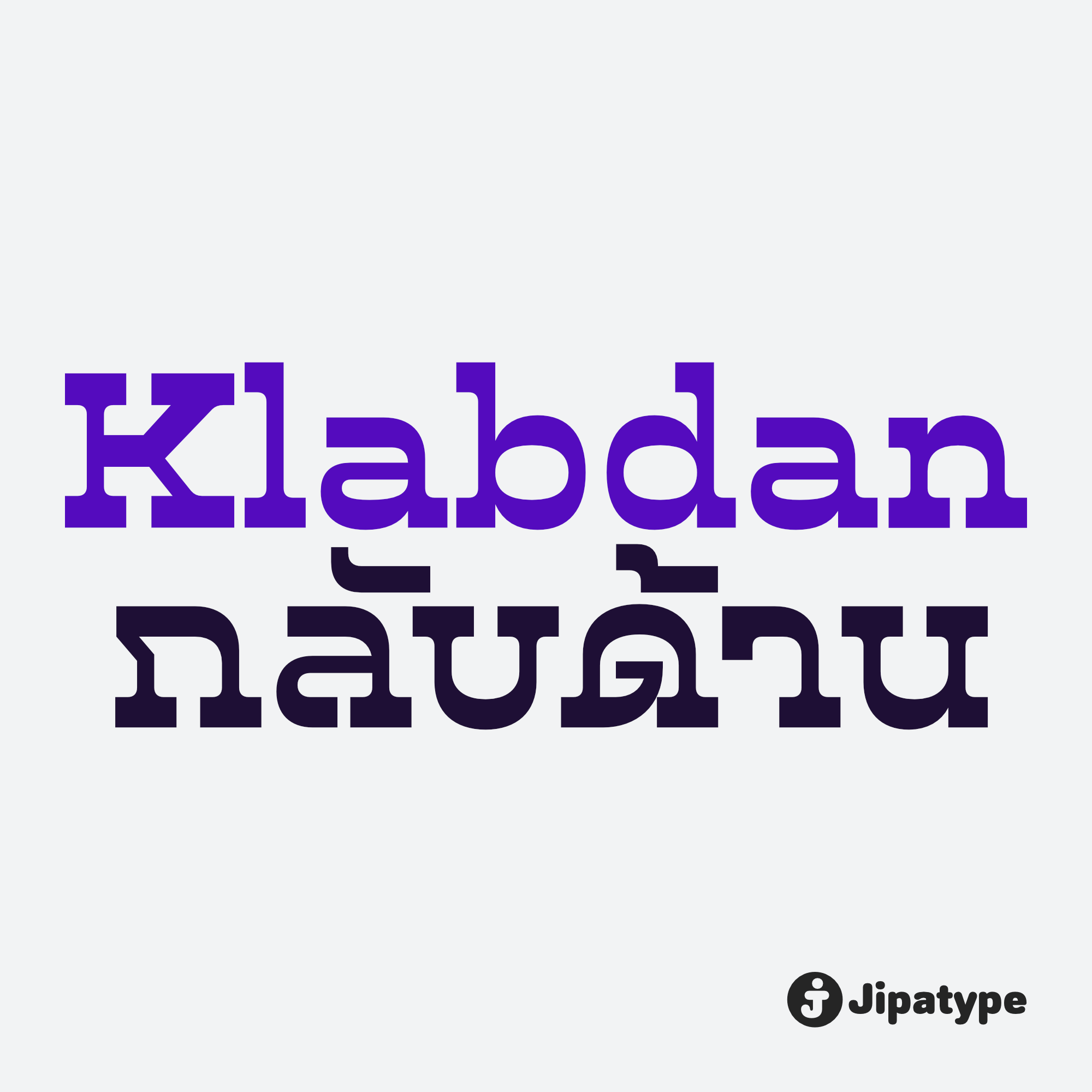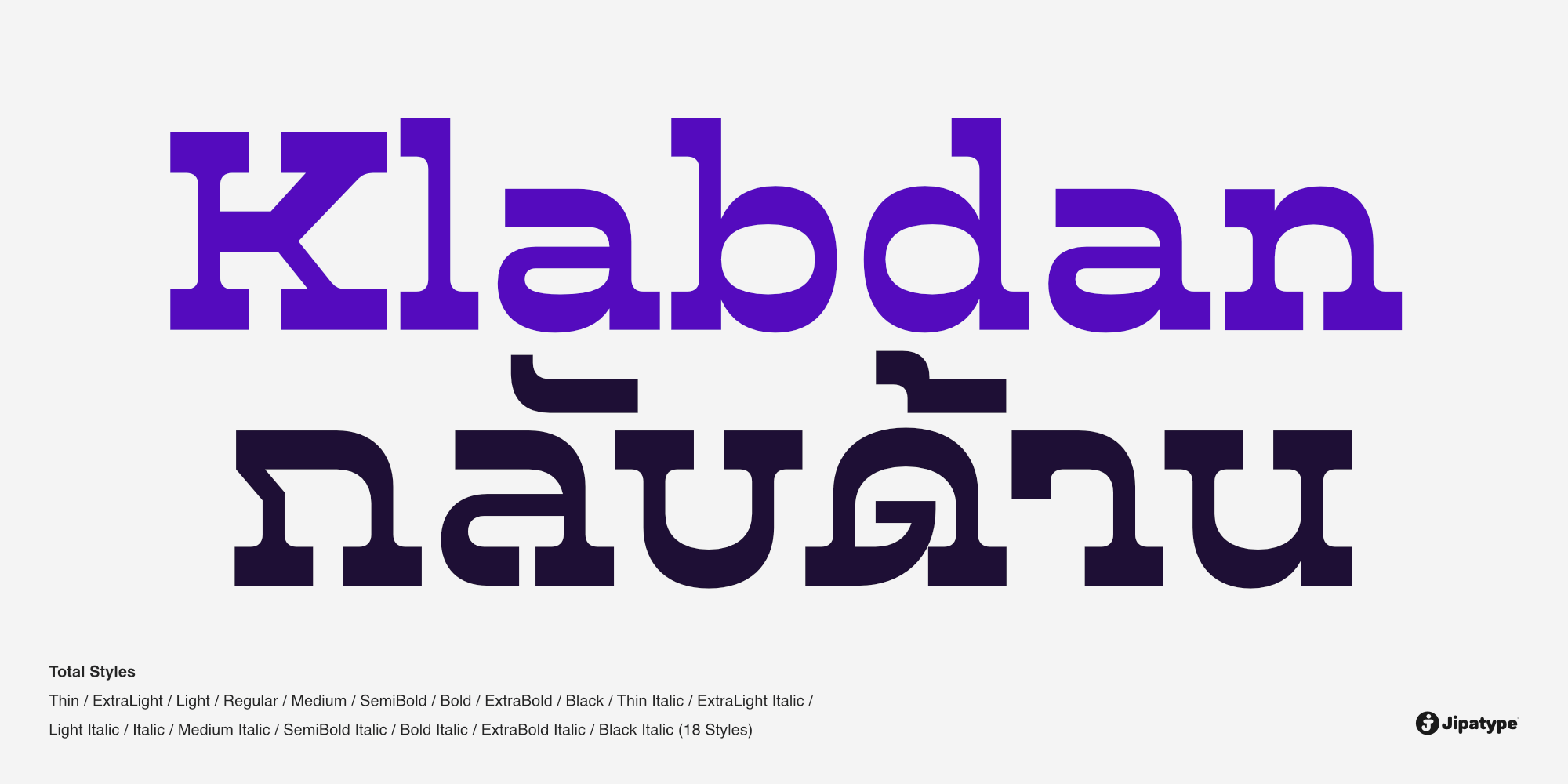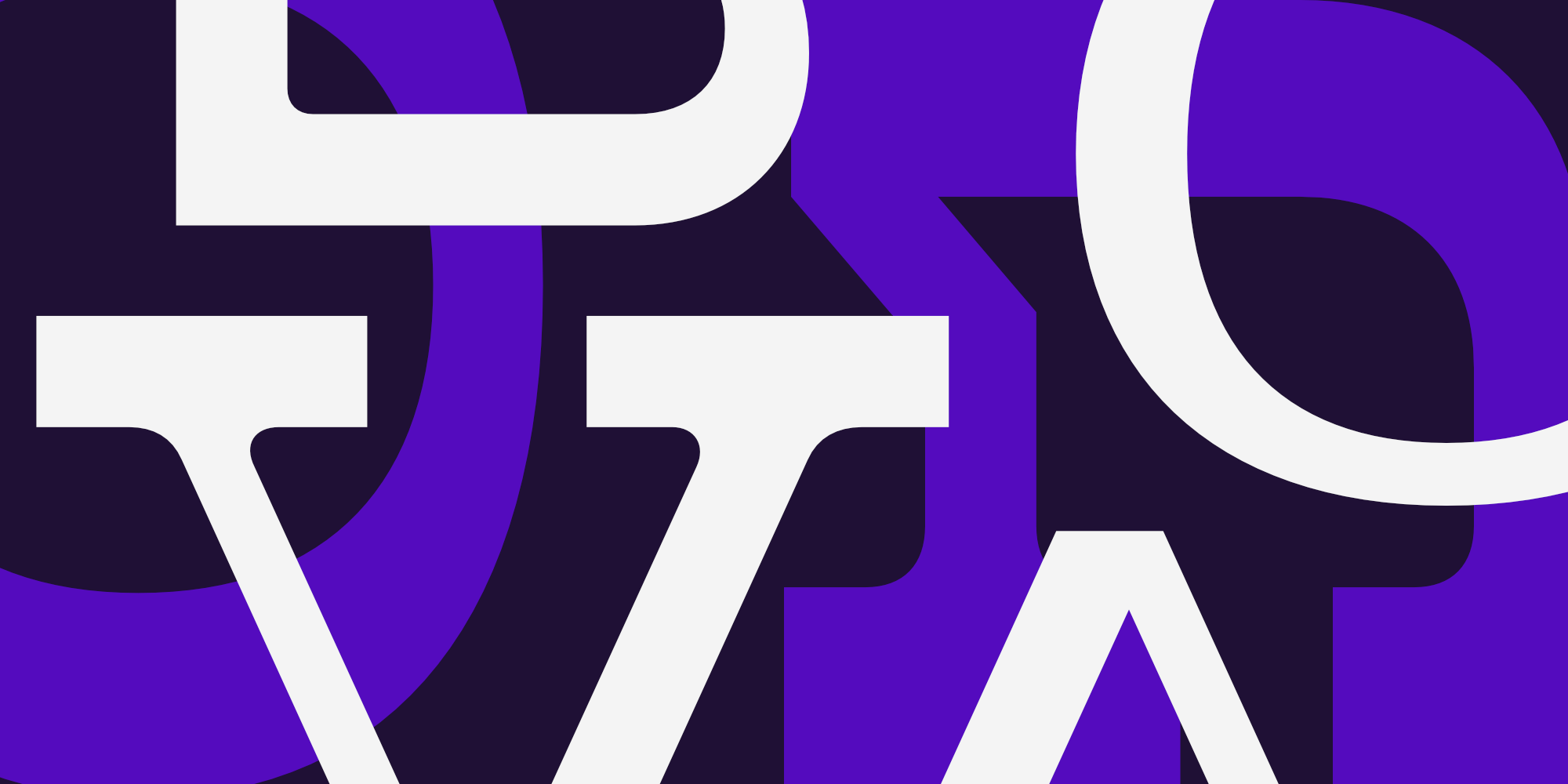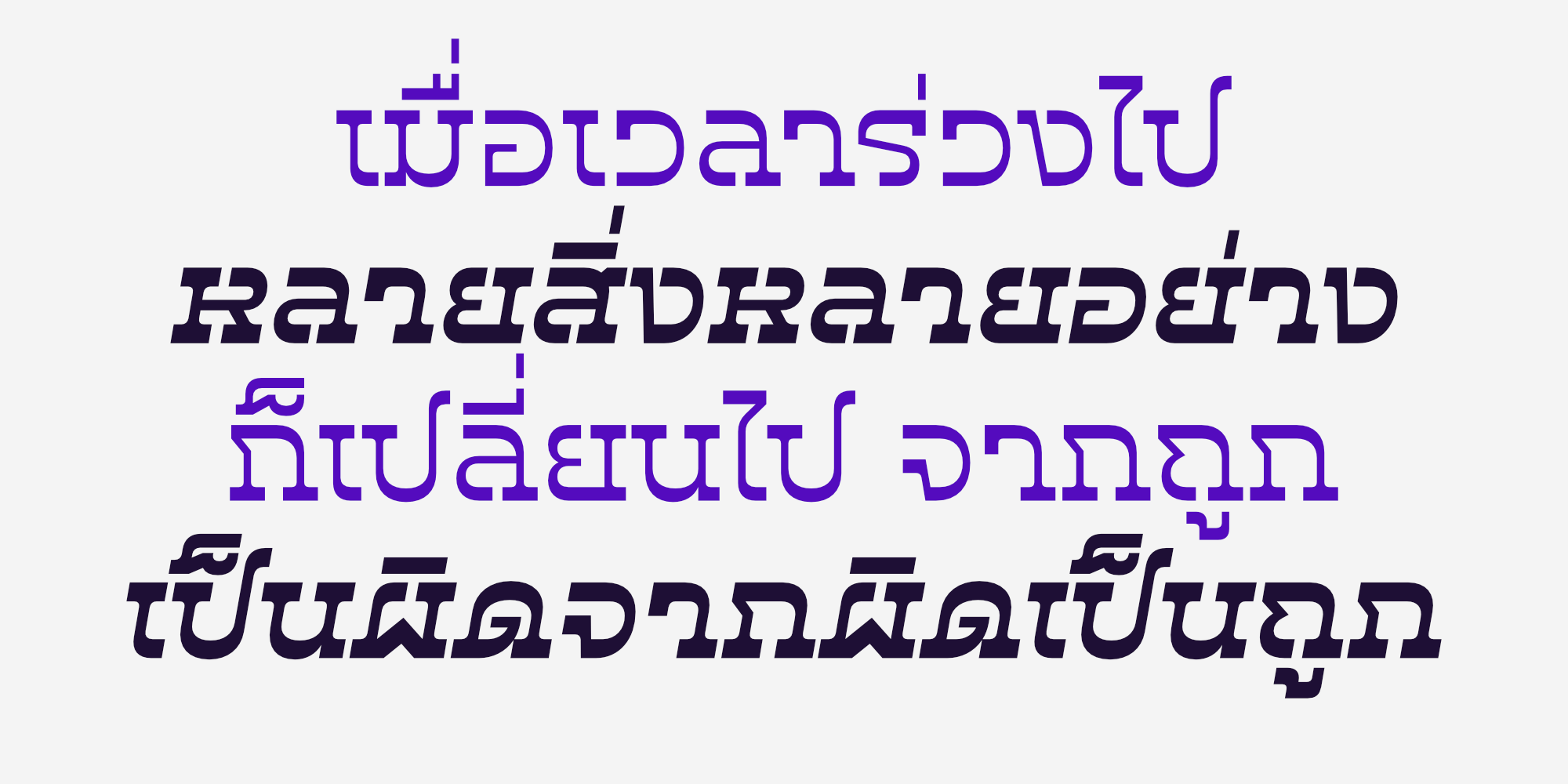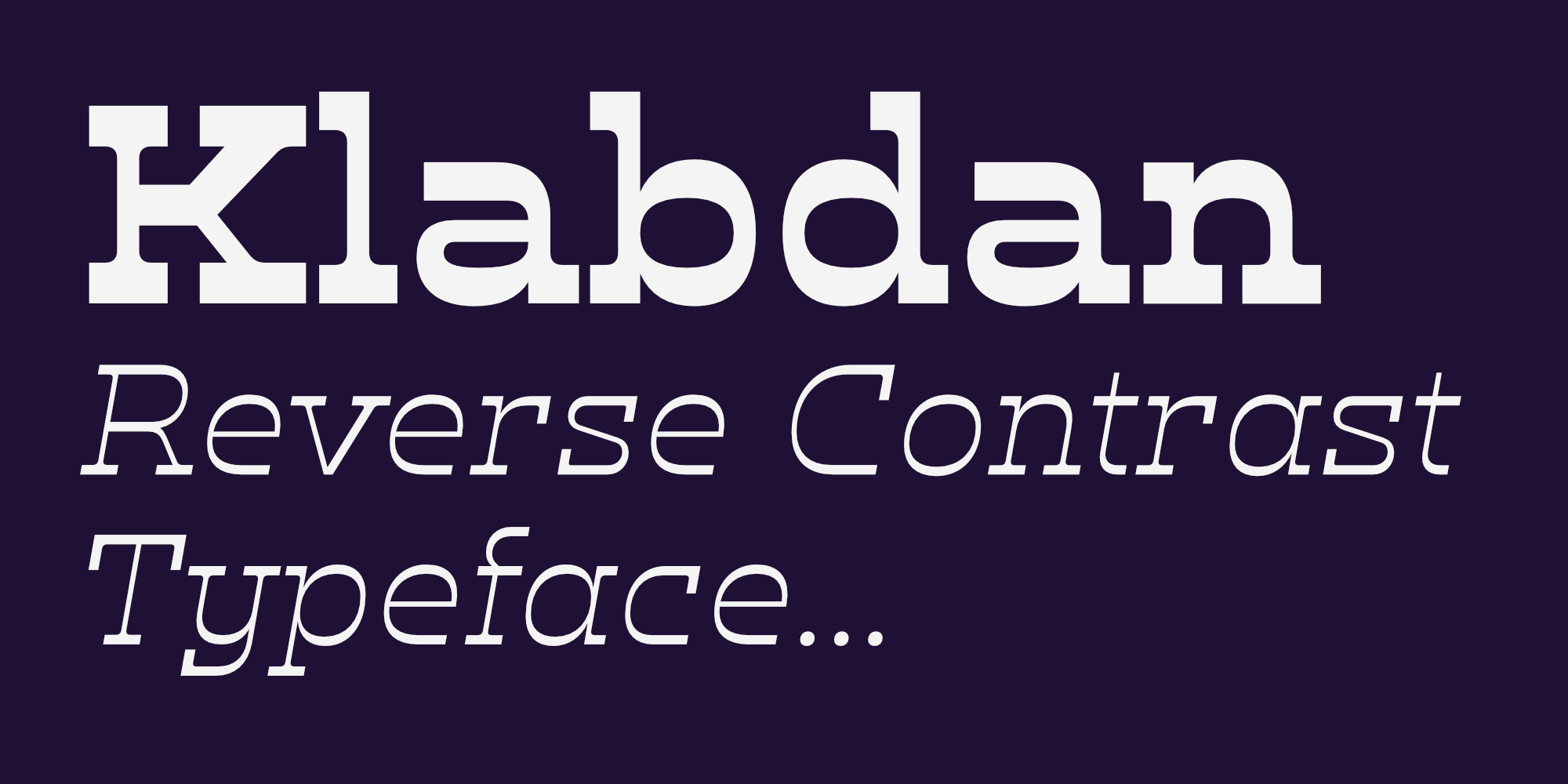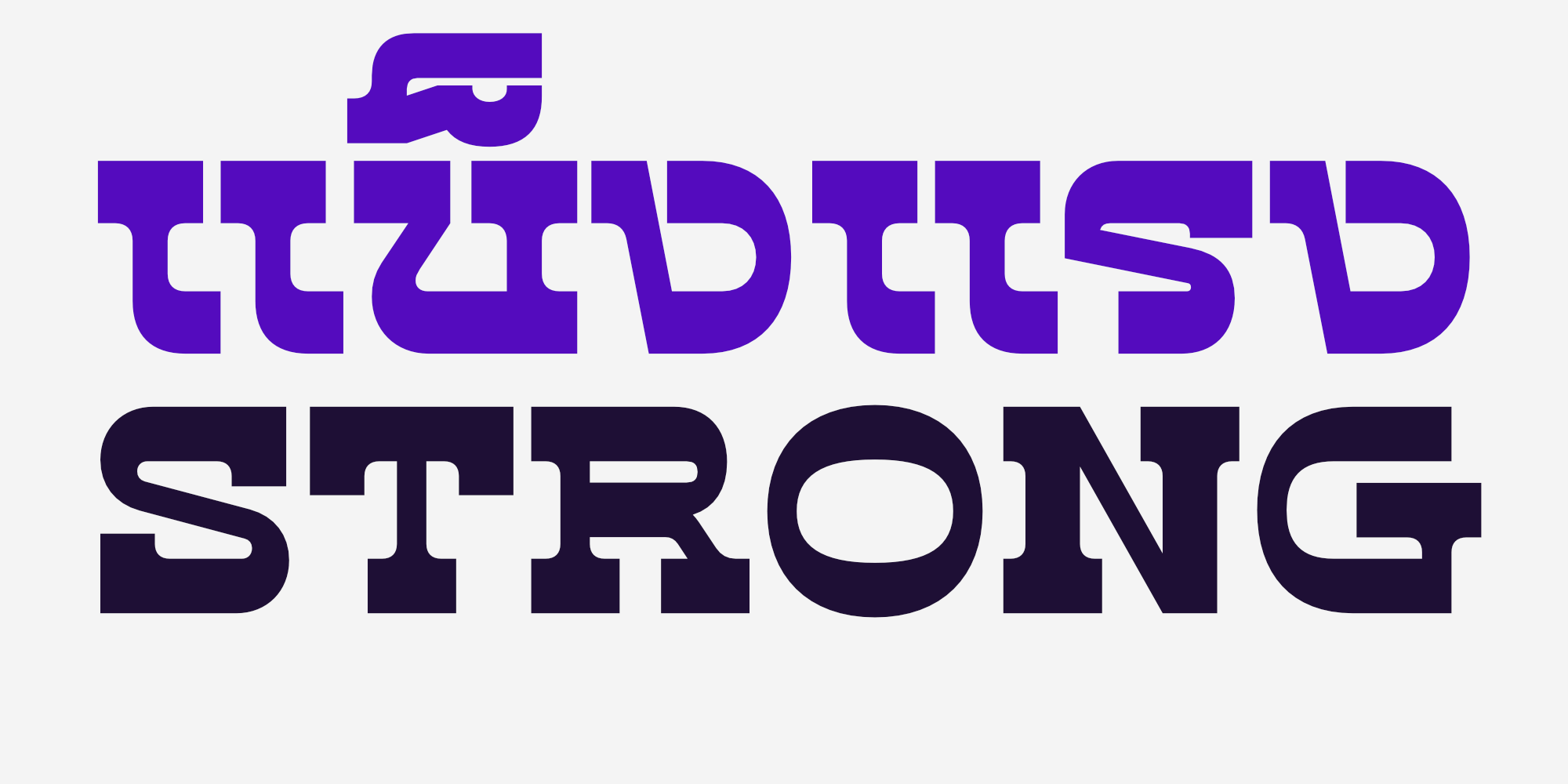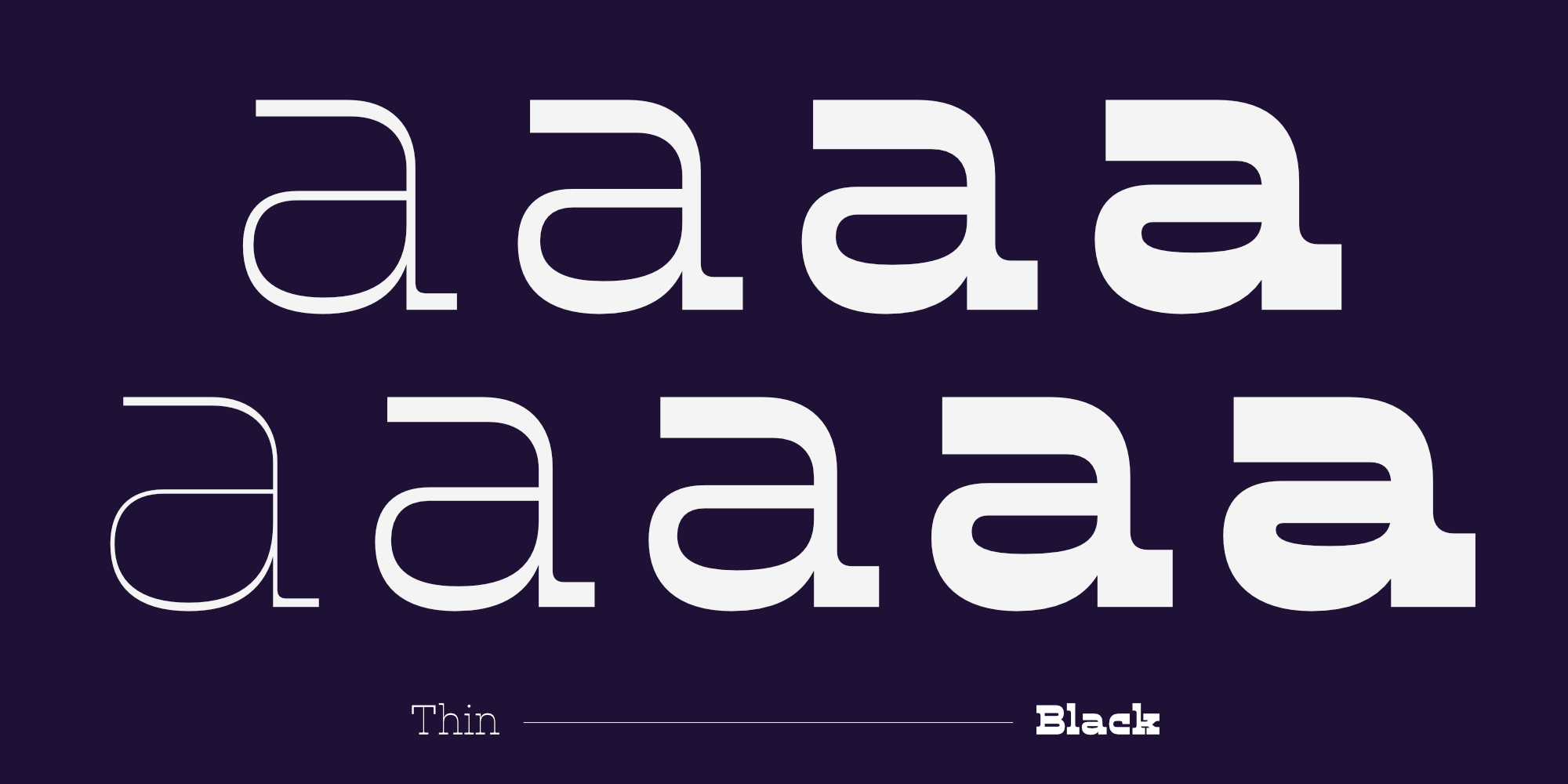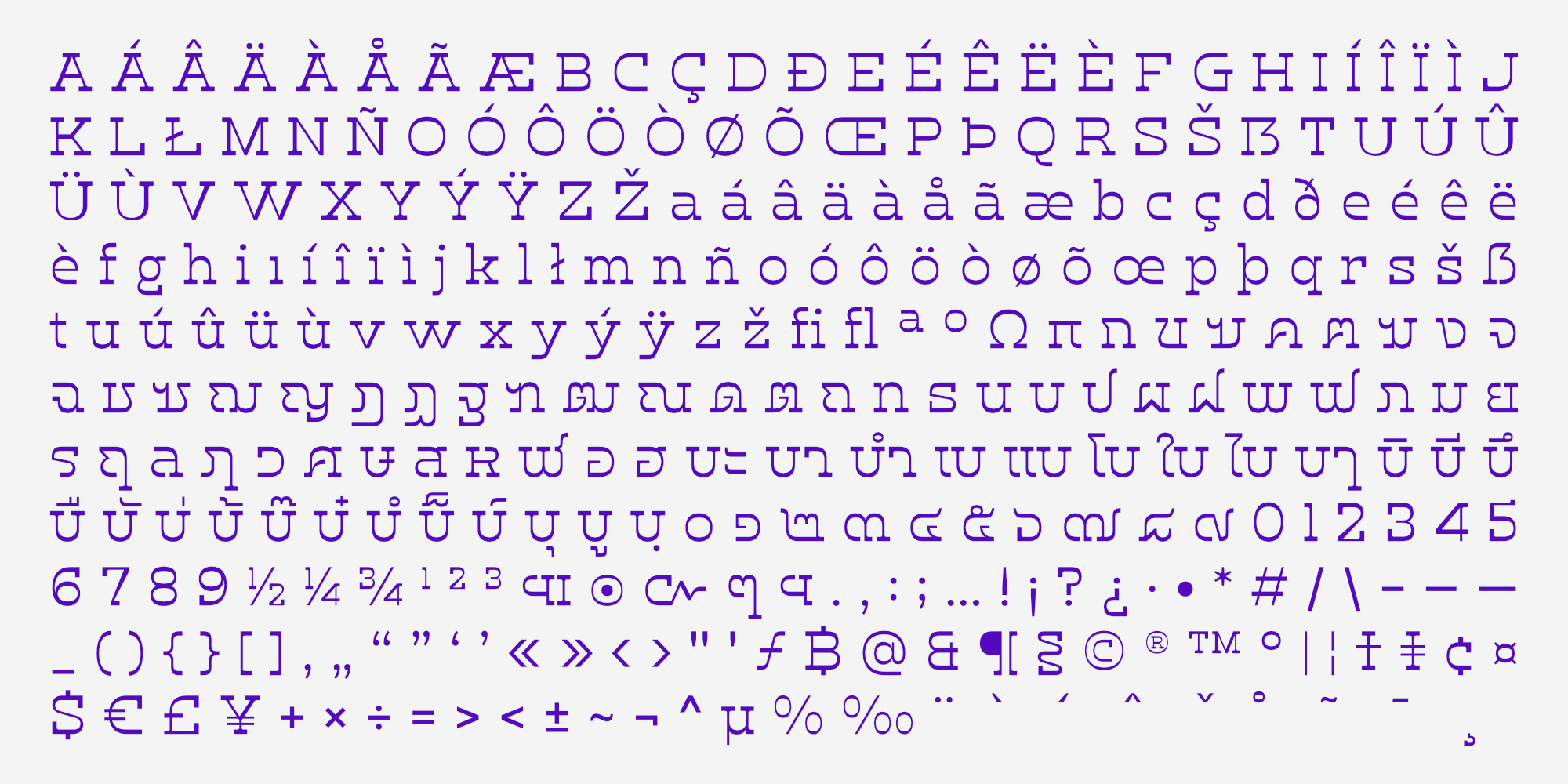
Klabdan (กลับด้าน) เป็นชุดตัวอักษรประเภท Reverse Contrast Slab Serif ที่มีเอกลักษณ์เฉพาะตัวสูง ด้วยการออกแบบที่ฉีกกฎเกณฑ์เดิม ๆ โดยการเน้นน้ำหนักของเส้นแนวนอนให้หนาและเส้นแนวตั้งให้บาง ประกอบกับฐานตัวอักษรแบบ Slab Serif ที่มีความโค้งมนเล็กน้อย ช่วยลดความแข็งกระด้างและเพิ่มความรู้สึกเป็นมิตร
ตัวฟอนต์ให้กลิ่นอายผสมผสานระหว่างความย้อนยุค และความร่วมสมัยที่ดูสนุกสนาน มาพร้อมกับชุดตัวอักษรภาษาไทยที่ได้รับการออกแบบให้มีสไตล์สอดคล้องกับตัวละตินอย่างลงตัว ทำให้ Klabdan เหมาะอย่างยิ่งสำหรับการใช้งานเป็นตัวพาดหัว งานออกแบบโลโก้ ป้ายร้าน โปสเตอร์ บรรจุภัณฑ์ หรือสื่อโฆษณาที่ต้องการสร้างจุดเด่น ดึงดูดสายตา และสร้างภาพจำที่แตกต่างไม่ซ้ำใคร
ออกแบบโดย : อานุภาพ ใจชำนาญ (Anupap Jaichumnan)